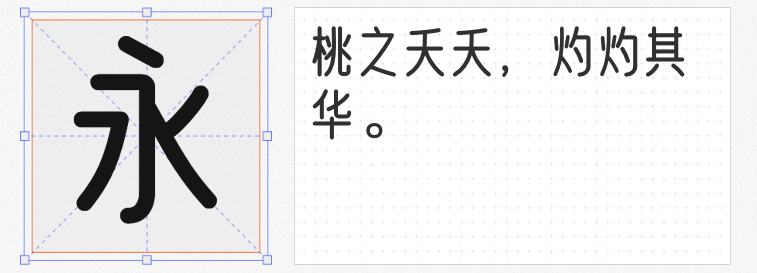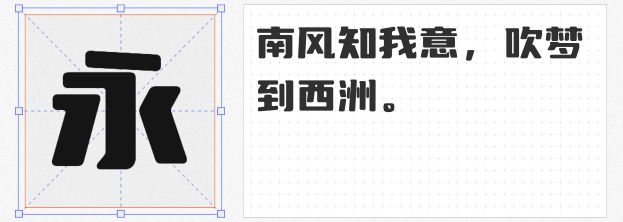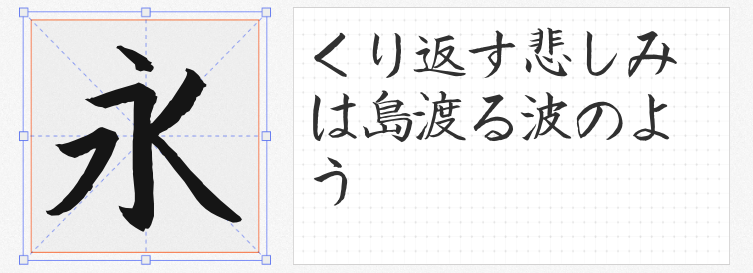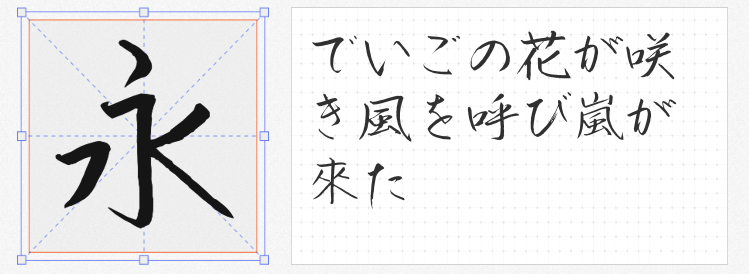
免费商用字库字体推荐:打造专业设计作品的优选
在设计中,字体的选择至关重要。它不仅影响着整体视觉效果,还能传达出特定的情感和氛围。今天,我为大家推荐四款免费商用字库字体,它们都是设计作品中的优选,既美观又实用。
1.英椎楷书
英椎楷书是日本acfont手写开发的一款字体,以其端庄雄伟、书写工整的特点而备受青睐。这款手写字体不仅具有极高的观赏性,还非常适合用于需要正式、庄重氛围的设计作品。虽然它是一款日文字库字体,但含有少量的简体中文字符,足以满足部分中文设计需求。
2.英椎行书
与英椎楷书同出一脉的英椎行书,同样展现了acfont手写开发的精湛技艺。这款字体同样端庄雄伟,书写工整,但相比楷书更加流畅自然,富有动感。它同样适用于需要正式氛围的设计作品,同时又能为作品增添一丝灵动与活力。
3.优设好身体
「优设好身体」是一款亲和力、现代感极强的专业美术标题字体。它以圆体字型为基础,通过瘦高的字面和偏向几何的曲线设计,让整款字体充满了亲和力和时尚感。这款字体非常适合用于设计作品的标题部分,能够迅速吸引观众的注意力,并留下深刻的印象。
4.优设标题圆
优设标题圆则是在优设标题黑的基础上进行了优化和改进。它将原本犀利的尖角转为圆角,更加体现了字体的柔和与温润。这款字体同样适用于设计作品的标题部分,能够营造出一种温馨、亲切的氛围,与观众产生情感上的共鸣。
这四款免费商用字库字体各具特色,能够满足不同设计作品的需求。无论是正式庄重的场合,还是富有创意和活力的设计项目,都能在这些字体中找到合适的选择。希望这些推荐能够帮助大家在设计作品中更好地运用字体,提升整体视觉效果和传达力。